眾籌中的「思緒重生體」(下稱重生體),是設計師陳靖軒Roy製作的一套繁體字。2020年立法會選舉,有議員找他設計字體作競選之用。他交過幾款創作,其一就是重生體。「那是我首次構思這款字,最初用『香港重生』四個字試著設計。」是四字心聲?「當年大家都有很多情緒吧。若天下太平,可能不會有重生體。」最終政府將選舉押後一年,「什麼設計都用不著了。」
往後他費時一年半發展重生體,製作過1,000字的試用版,今次眾籌想進一步設計5,300字的版本。「近廿年香港都沒什麼新的繁體電腦字。現在香港的文化和靈魂被蠶食,是不爭的事實。幾時冇得再用繁體字?冇得再講廣東話?未知。與其失去才後悔,不如呢刻就做好繁體字。」哀莫大於冇得揀,多一款字,也是多一種選擇。
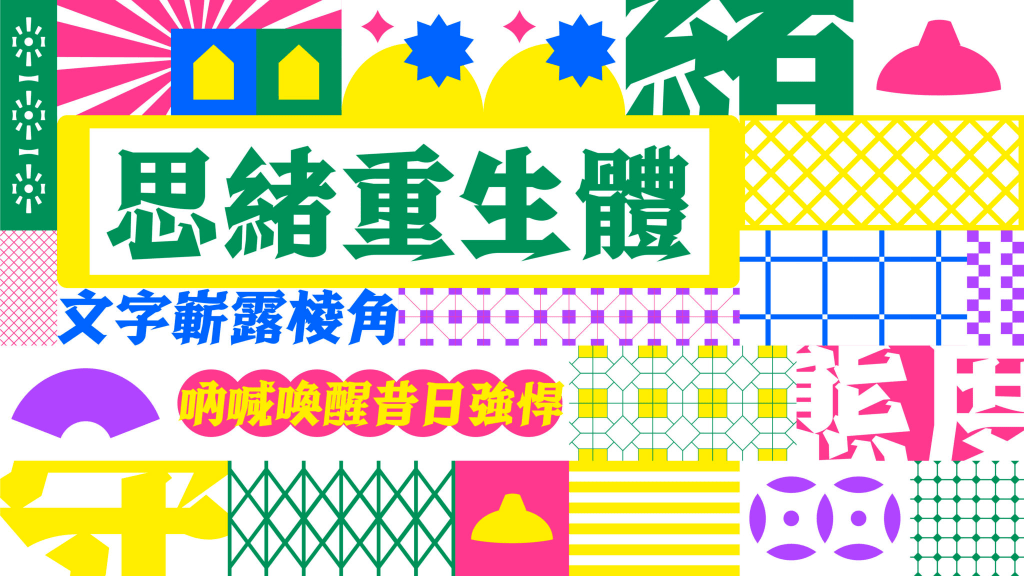
登上達明舞台 一套字的可能性
思緒重生體計劃製作的5,300字,包括「啱」、「啲」、「咁」等香港口語,大家打message用得多,但畀錢買字,自然沒買餸那麼普遍。買家通常是誰?如眾籌網所介紹,設計師、YouTuber、剪接師、動畫師等行業,統統需要用到字體。去年Roy曾發售重生體的千字試用版,出乎他意料,有設計師將字體用於《達明一派REPLAY LIVE 2021》演唱會的video wall上。雖然Roy不在現場,「但有人cap圖給我看,真係嚇親,覺得好靚!一套字的功能就是這樣,讓人自由地運用,令我keep住對字體、對未來有想像。」
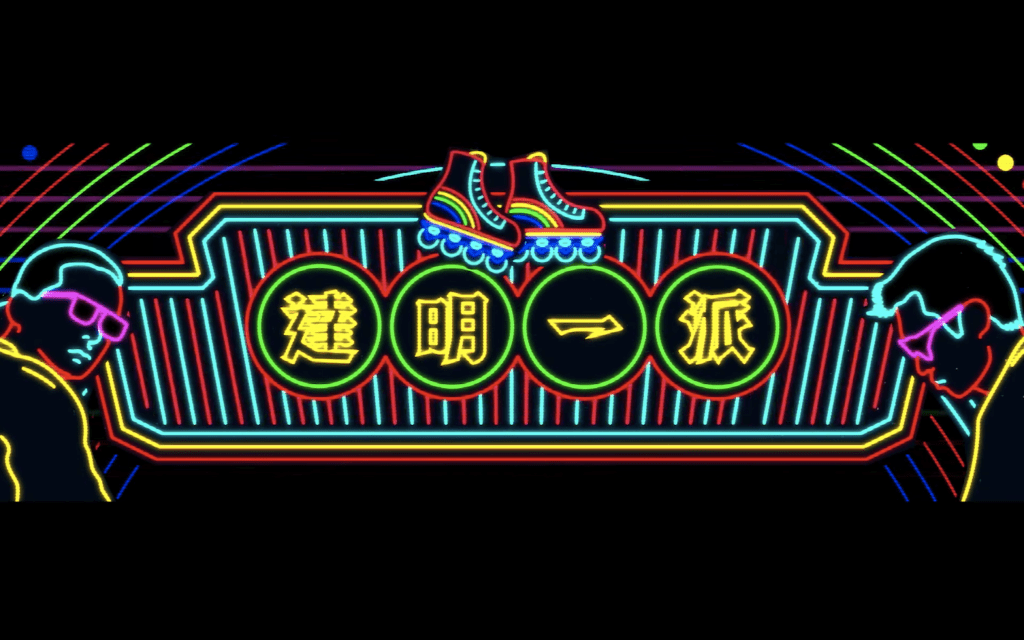
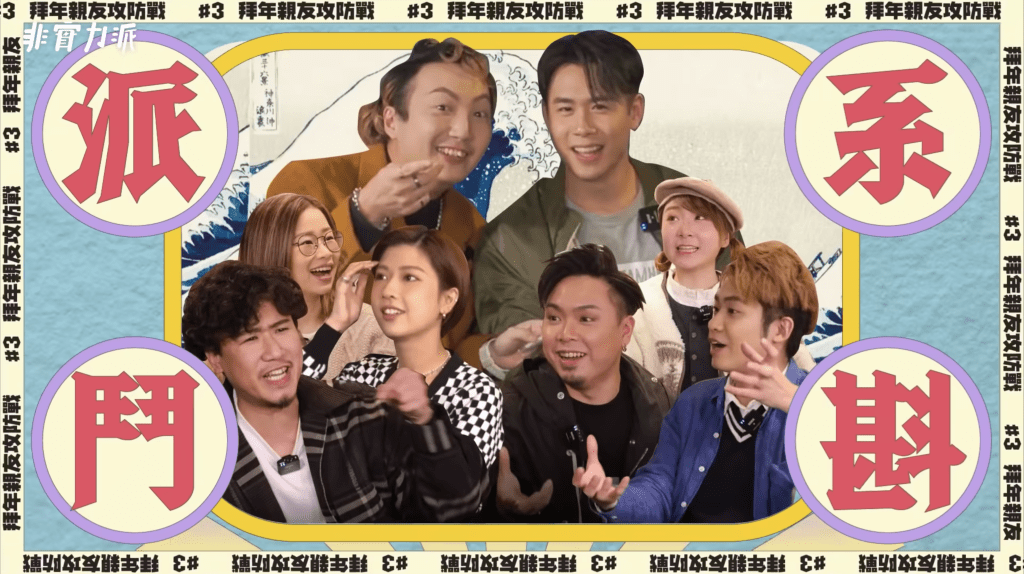
後來與video wall設計師聯絡上,對方形容重生體「配合懷舊或現代設計都非常適合」,這也是Roy想做到的。Technical地解釋,他的設計概念是:「結合宋體和黑體。宋體在舊式印刷術已存在,黑體則在電子化年代,於電子屏幕常用的,我希望做到新舊交融的感覺。」他的字體設計公司「思緒俠造字」2019年成立,「現在除了我,還有另一位設計師,加上負責文案和廣告等同事,約5人做重生體的campaign。」
他笑說:「如果有錢就不用眾籌啦!」小公司過往曾推出產品,包括以「飲」字為造型的開瓶器、印有不同字句的iPhone機殼和月曆等,展示Roy創作的各款字體。不過設計幾粒字的句子,與製作一套5,300字的重生體,規模與成本差得遠:「可能冇錢賺㗎!但繼續設計產品,都只是one-off的事,所以我想造一套字,能留下來讓更多人使用,然後承傳下去。」
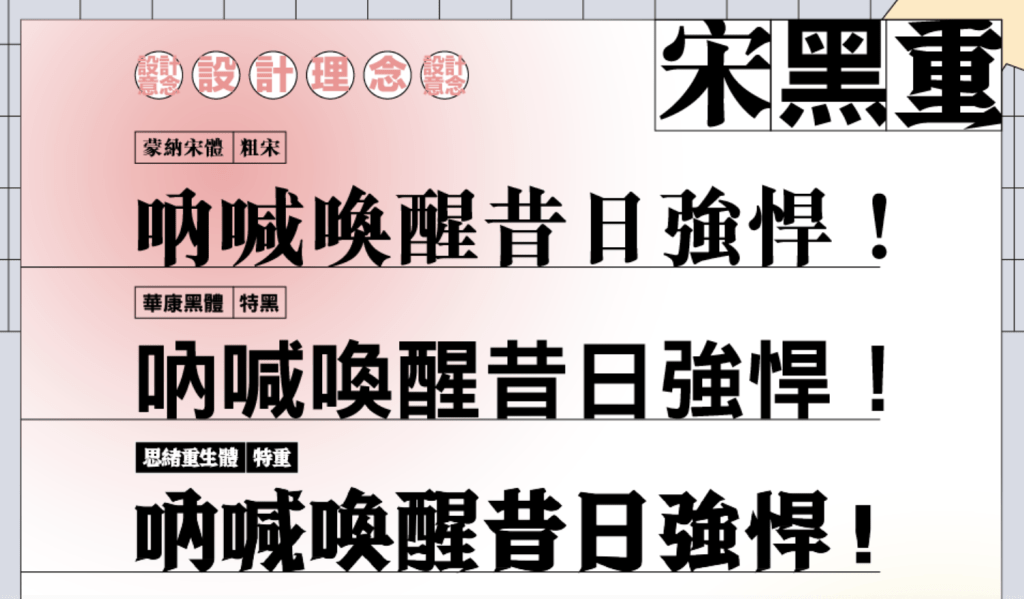
如果字型是一個人,思緒重生體像極穿著復古衣服的潮流大叔,帶點懷舊,卻絲毫沒有脫節之感。Roy說:「我哋希望做到一種fashion,無論係舊嘅(領域)又用到,新嘅都會用到」。他也希望港人能夠新舊交融,化解世代之爭,「老一輩同後生嘅矛盾,係咪唔可以和解呢?其實係想叫大家一齊搵返嗰種香港靈魂」。
用字體將聲音帶出來
現在聽來鴻圖大志,當初Roy成立公司,原來無心插柳。他讀廣告設計出身,曾在音樂平台KKBOX、電影發行公司做平面設計師,不時遇上「缺字」苦況。「譬如好靚的日文字體,當中有些漢字可以拿來用,但某些字始終與中文寫法不同,我就自行拼湊字的部首和部件,造字出來。」歸根究底,他說繁體字體原本就選擇不多。到2018年中,他的造字癮延伸至個人IG,開始將自己設計的字配圖出post,談生活感受。「朋友提議不如正式開個page,甚或推出產品,可能有人鍾意呢?」
思緒俠造字IG就這樣出現,由社運那些年至今,字圖post不乏港人心聲。「我最深刻是『發夢』那個post吧。」翻看該post,當時caption寫著:「我最近經常【發夢】/喺個夢入面我夢想成真/而我的夢想是/香港是香港。」他形容重生體在設計上,是「有力量」的字體,回想初稿早於2020年出現,「當時我覺得大家都需要團結、有力的感覺,而字體可以將這種聲音帶出來。」
近年香港偶有獨立造字人出現,如設計師Kit Man製作「勁揪體」,或前元朗區議員陳敬倫所創的「爆北魏體」,分別在2016年和去年尾展開眾籌,最終兩者都成功。「行家」人少少,Roy與陳敬倫因字相識,笑指大家還夾過時間,前後腳眾籌。「少人做,因為困難。」撇除粒粒皆辛苦又費時的造字工程,「教育大家要畀錢一買套字,難;叫人在眾籌階段先畀錢,等我半年後完成才『出貨』,就更難。」
他還是要試。「想保育繁體字。大陸好多軟實力來港,他們的公司會用簡體字。或者你現在沒有危機感,但好多嘢,冇咗才怨天尤人已沒用。」不是說一套字能改變世界,「但我想畀人知,在不犯法的情況下,每個人仍有很多事可以做。」